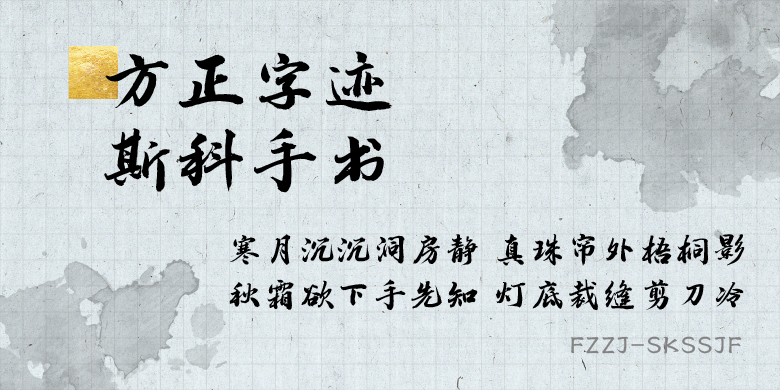
方正字迹-斯科手书
字体品牌: 方正字迹 设计师:李斯科 字体分类:创意书写 字体属性:精品字 字符集:大陆简体(GB2312-80)、简繁扩展(GBK) 发布时间: 2021
此款字体是作者在2019写的,根据自己的书写习惯,加上对传统书法的敬畏和现代手写的理解进行提炼再揉合,字体主要立足于行楷体,但结构和笔画都要比传统行楷更为灵活,且比目前市面上大多数豪放不羁的手写字库要收敛很多,笔法方圆并存,线条粗细适中,辩识度较强。旨在达到一种既国风文艺又现代时尚的观感。
作者李斯科,墨研社(中国水墨研究社)成员、商业书法字体设计师、方正字库签约设计师。